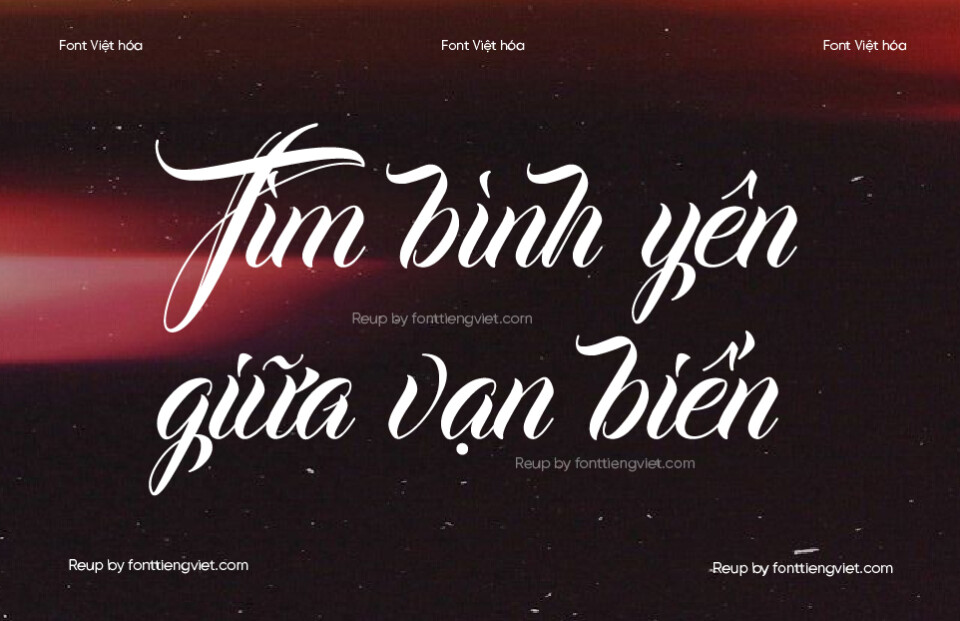
Giới thiệu về Font Việt hóa UTM Bandung
Trong thế giới thiết kế đồ họa hiện đại, việc lựa chọn một bộ Font Chữ phù hợp đóng vai trò quyết định đến tính thẩm mỹ của sản phẩm. Font Việt hóa UTM Bandung là một trong những lựa chọn hàng đầu dành cho những ai yêu thích phong cách script phóng khoáng và nghệ thuật. Được phát triển dựa trên cảm hứng từ những nét chữ viết tay uyển chuyển, bộ font này mang lại cảm giác gần gũi nhưng không kém phần sang trọng. Đặc biệt, phiên bản UTM Bandung đã được tối ưu hóa đầy đủ dấu tiếng Việt, giúp các bạn học sinh và nhà thiết kế dễ dàng ứng dụng vào các bài thuyết trình hay dự án cá nhân mà không lo lỗi hiển thị.
Đặc điểm nổi bật của Font Việt hóa UTM Bandung
Phong cách thiết kế độc đáo
Font Việt hóa UTM Bandung sở hữu các đường nét thanh mảnh, uốn lượn tự nhiên giống như những nét vẽ bằng cọ lông. Sự kết hợp giữa các ký tự cao thấp không đều tạo nên một nhịp điệu sinh động cho văn bản. Đây là công cụ đắc lực để tạo ra những tiêu đề ấn tượng hoặc các đoạn trích dẫn giàu cảm xúc trên mạng xã hội.
Tính ứng dụng đa dạng trong học tập
Với các bạn học sinh, bộ font này cực kỳ hữu ích khi làm báo tường, thiết kế thiệp chúc mừng thầy cô hoặc trang trí bìa tập. Độ tương phản giữa các nét đậm nhạt giúp nội dung trở nên nổi bật và thu hút thị giác ngay từ cái nhìn đầu tiên. Ngoài ra, font còn hoạt động mượt mà trên nhiều phần mềm thiết kế chuyên nghiệp lẫn văn phòng thông dụng.
Kết luận và cách sử dụng hiệu quả
Việc sở hữu Font Việt hóa UTM Bandung sẽ giúp bộ sưu tập tài nguyên sáng tạo của bạn thêm phong phú. Để đạt hiệu quả tốt nhất, bạn nên kết hợp font này với các phông chữ không chân (sans-serif) đơn giản nhằm tạo sự cân bằng. Hãy tải ngay bộ Font Miễn Phí, Font Việt Hóa, Font Việt hóa UTM Bandung để trải nghiệm sự khác biệt và nâng tầm các tác phẩm thiết kế của mình ngay hôm nay.